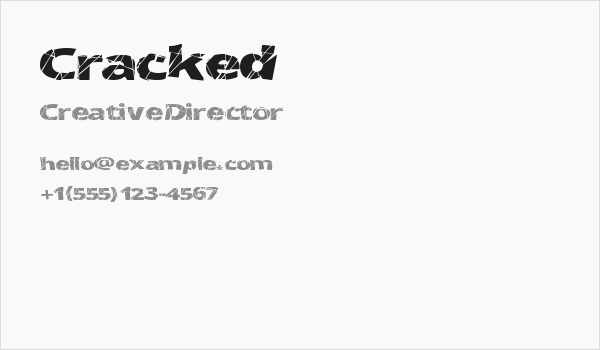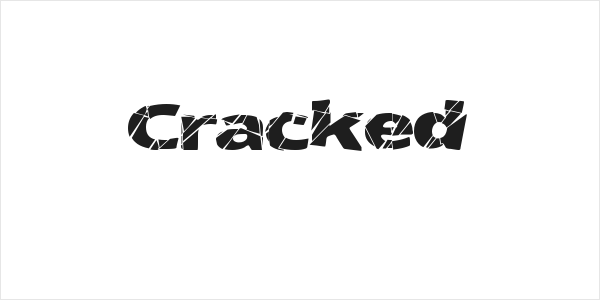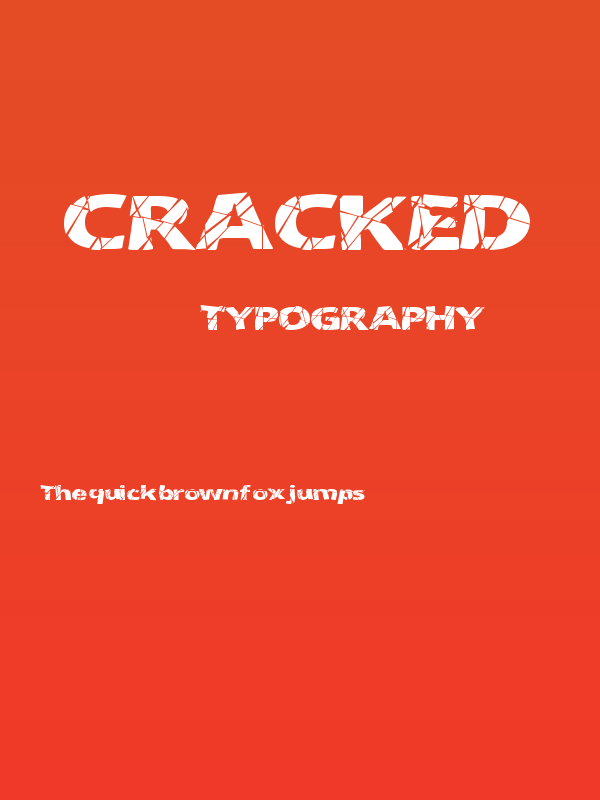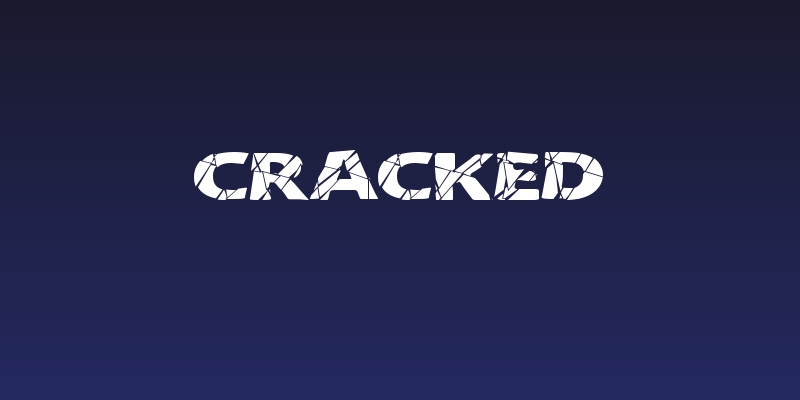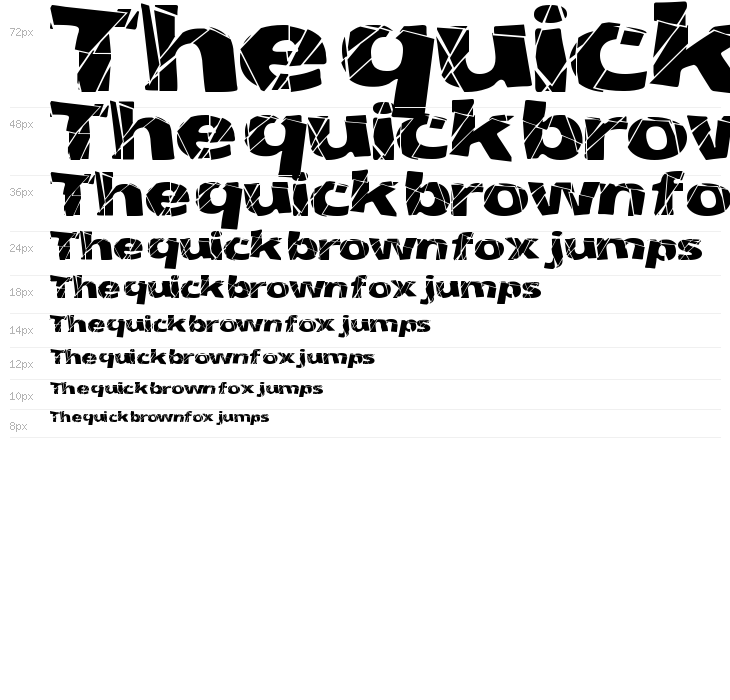
Cracked Font
✎ Distorted Eroded
| Projetos propostos | Ideal for album covers, event posters, graffiti art, and branding for extreme sports or urban-themed businesses. |